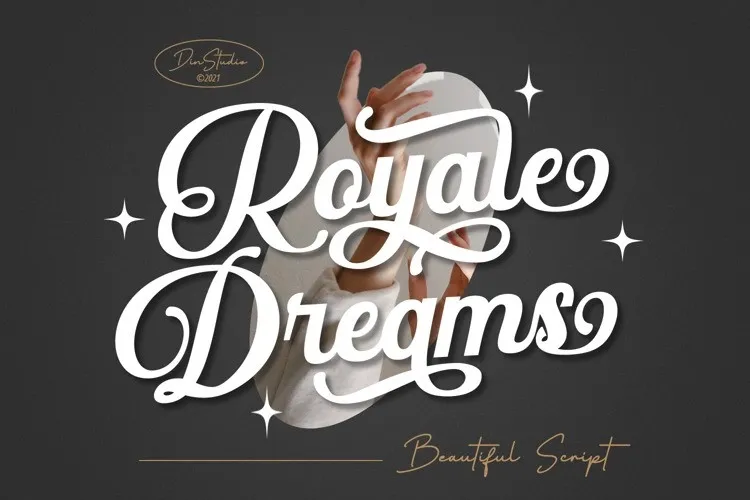
A Royale Dreams Font é uma elegante tipografia script criada pela Din Studio, repleta de estilos alternativos, ligaturas, swashes e caracteres multilíngues. Esta fonte agradável aos olhos excelsa na captura de headlines grandiosos ou texto de marcação grande, transmitindo aquela sensação adoravelmente cutesa que faz você dizer “aww!”. Ideal para projetos de design gráfico, seja ele em redes sociais, campanhas de marketing digital ou elementos visuais que desejam capturar a atenção e transmitir um toque delicado e encantador. Seria uma escolha perfeita para quem busca algo único e vibrante, mas ainda assim deseja manter um padrão de elegância nas suas criações.